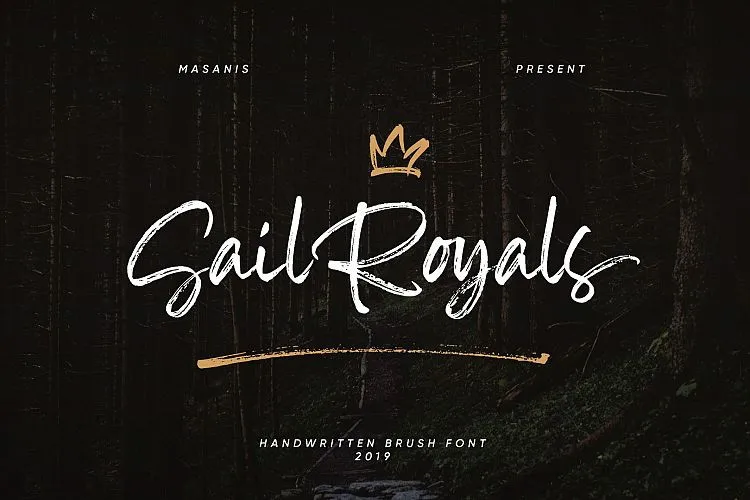
Sail Royals Brush Font – Download Grátis
A Sail Royals Brush Font é uma nova opção para designers que buscam adicionar um toque autêntico a seus projetos. Criada pelo designer 0001themes, esta fonte script remete diretamente aos desenhos feitos à mão com um pincel de tinta, capturando detalhes meticulosos e dinâmicos nas escritas largas e textos mais detalhados. Ideal para aplicação em grandes encabezamentos ou lembretes, esta fonte também oferece uma grande variedade de possibilidades ao escrever parágrafos extensos. Com traços rápidos e estilo distintivo, a Sail Royals é perfeita para projetos de marca, design de móveis de casa, embalagens de produtos – ou mesmo como um texto elegante sobre qualquer fundo, como imagens de citações. Com seu ar pessoal e seu formato vectorizado cuidadosamente moldado, esta fonte ajuda a criar um efeito único em seu trabalho gráfico. A cada letra foi desenhada com um pincel real em papel para garantir que as características naturais da escrita à mão sejam mantidas. O resultado é uma combinação de personalidade única e controle profissional, perfeita para quem busca dar vida a suas ideias através de textos estilizados.